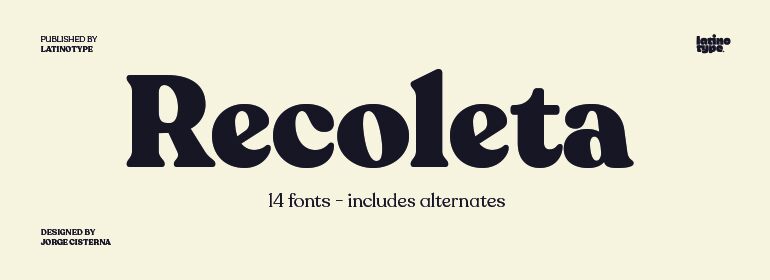
Wie Omas Geheimrezept kombiniert Recoleta verschiedene Zutaten beliebter Schriften der 70er Jahre – etwa die weichen, sanften Formen von Cooper oder die flüssigen, angewinkelten Striche von Windsor. Das Ergebnis ist ein Design, das vertraut und doch frisch und modern wirkt.
Die Vielfalt der Strichstärken bietet eine große Auswahl, mit der Sie genau den richtigen typografischen Ton für Ihr Projekt finden. Die leichteren Schnitte eignen sich hervorragend für den Fließtext, während die schwereren ideal für wirkungsvolle Überschriften sind. Die verfügbaren stilistischen Alternativen bieten zahlreiche Sonderzeichen, die Ihrem Logo oder Ihrer Visitenkarte eine unverwechselbare Note verleihen.
Jorge Cisterna